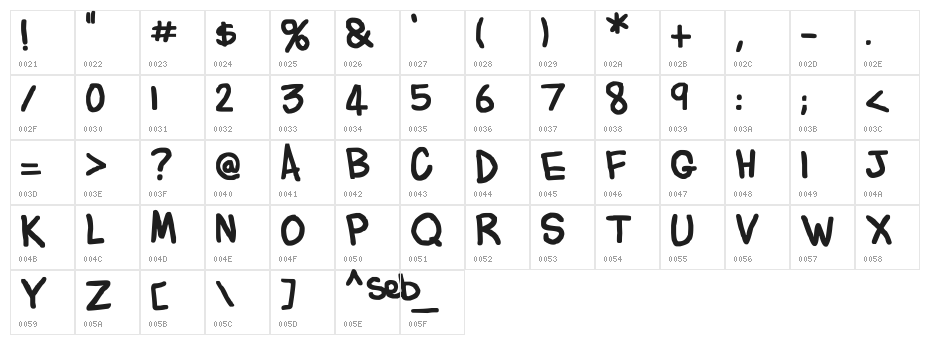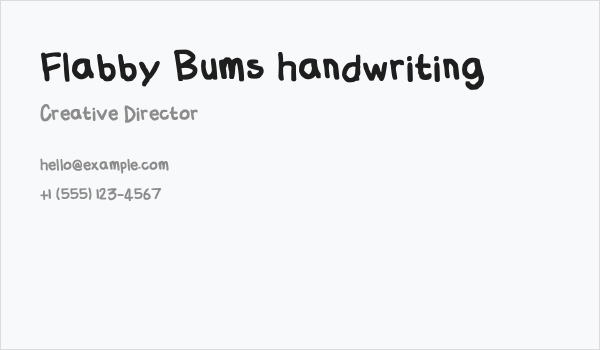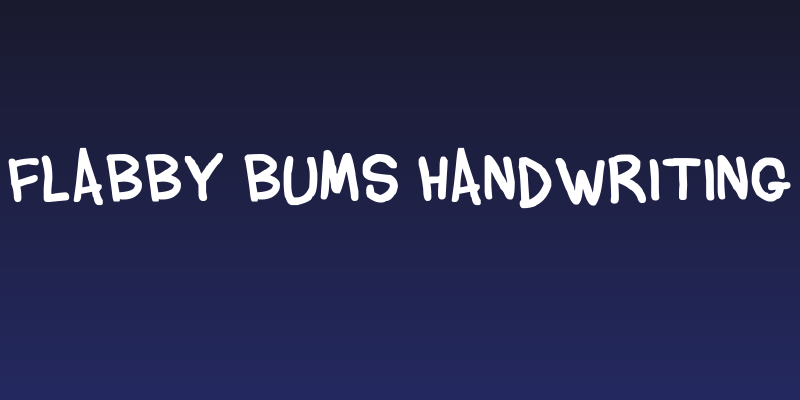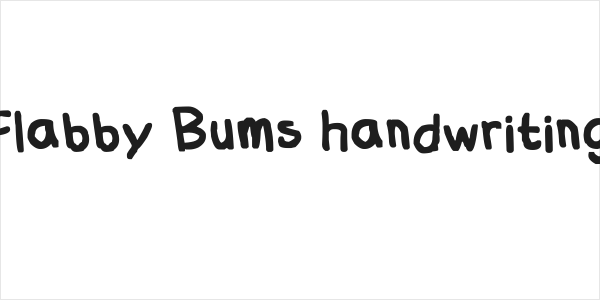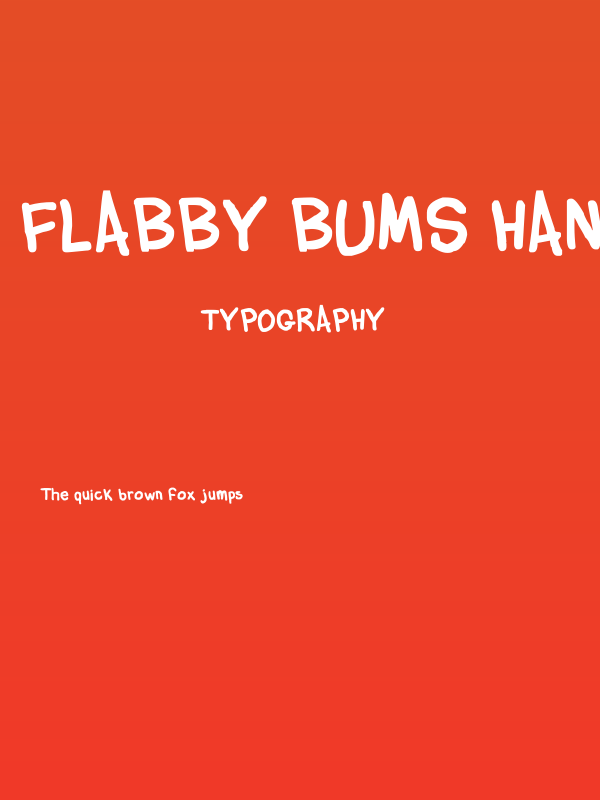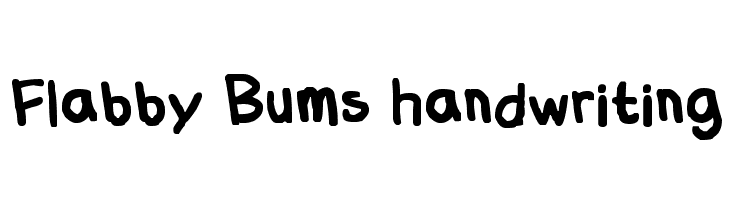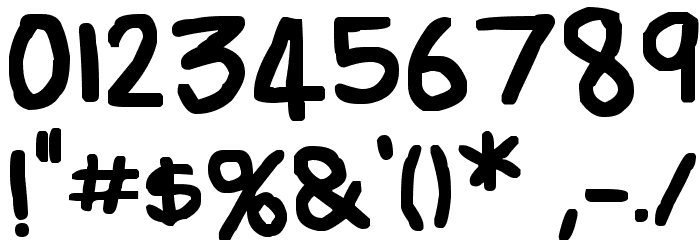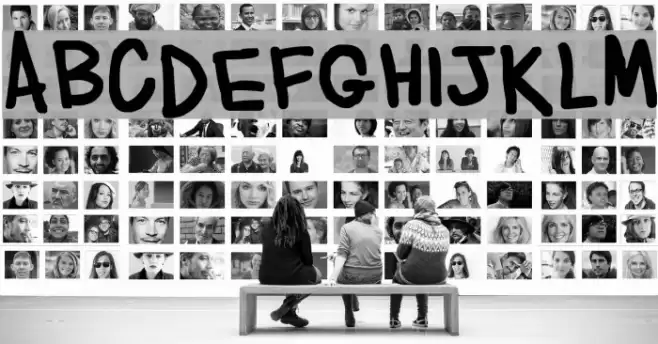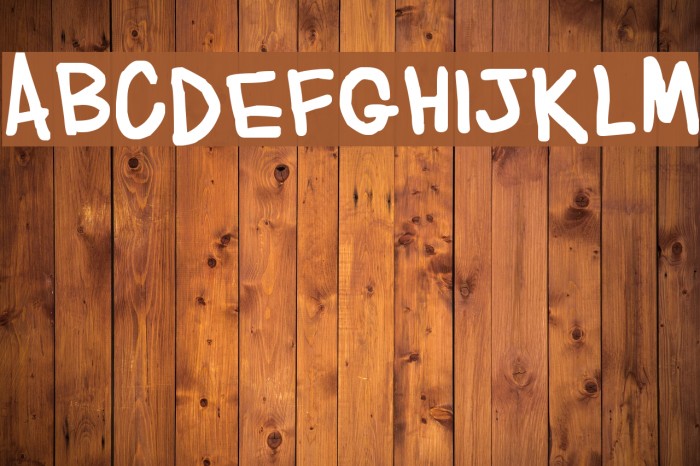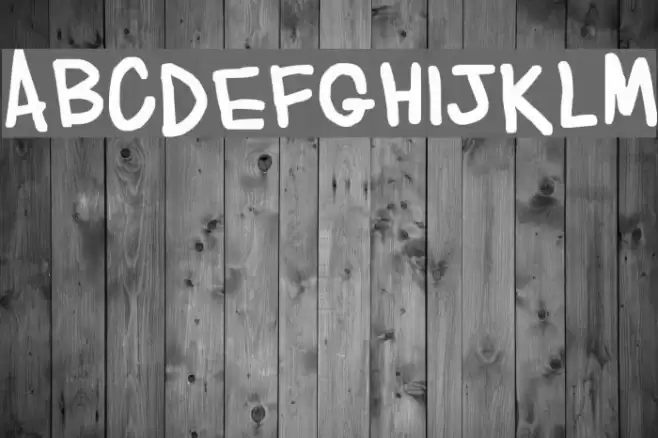
Flabby Bums handwriting Font
| 用途 | Headlines, Logos, Informal Text |
| おすすめプロジェクト | Ideal for children's books, playful branding, greeting cards, and casual invitations. |